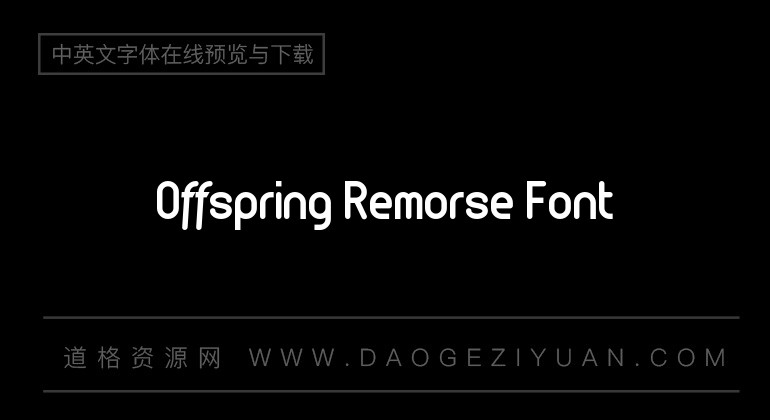
Offspring Remorse Font
Offspring Remorse Font 是一种受到黑体字体和手写字体启发的字体。它的设计风格独特,带有一些草图和自然笔画的感觉,同时也保持了黑体字体的稳定和清晰。该字体具有良好的可读性,特别是在较小的字号下。 Offspring Remorse Font 适用于许多用途,如标志、包装设计、海报、传单、标题和正文。该字体的设计者意图是提供一个新鲜、有趣和独特的字体,适合那些寻求与众不同的设计师和品牌。 该字体可以在许多在线字体库和商店中获得,也可以在一些字体设计工具中找到。如果你正在寻找一种具有独特风格但易于阅读的字体,Offspring Remorse Font 可能是一个不错的选择。
Offspring Remorse Font是一款非常不错的手写艺术字体,具有很好的视觉感,适合于文化类的宣传设计、商业类品牌的广告和产品包装设计以及个性化文字排版等较多场景。